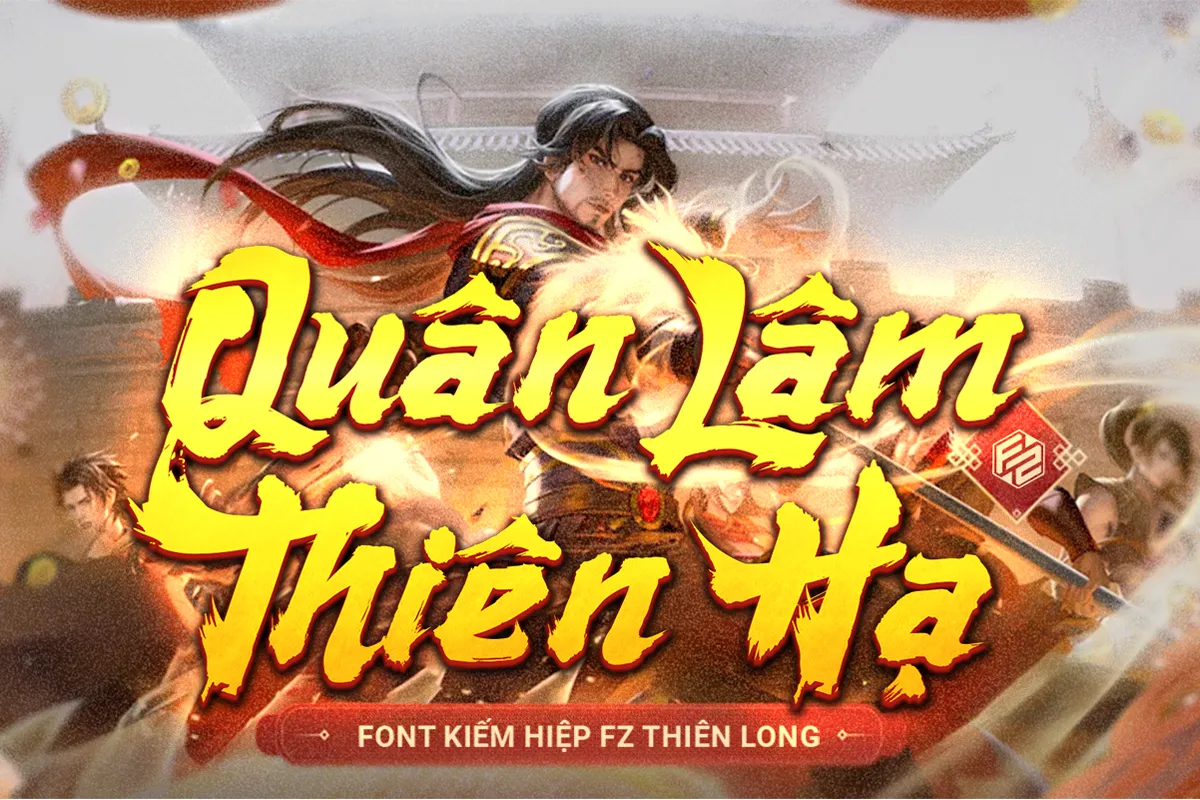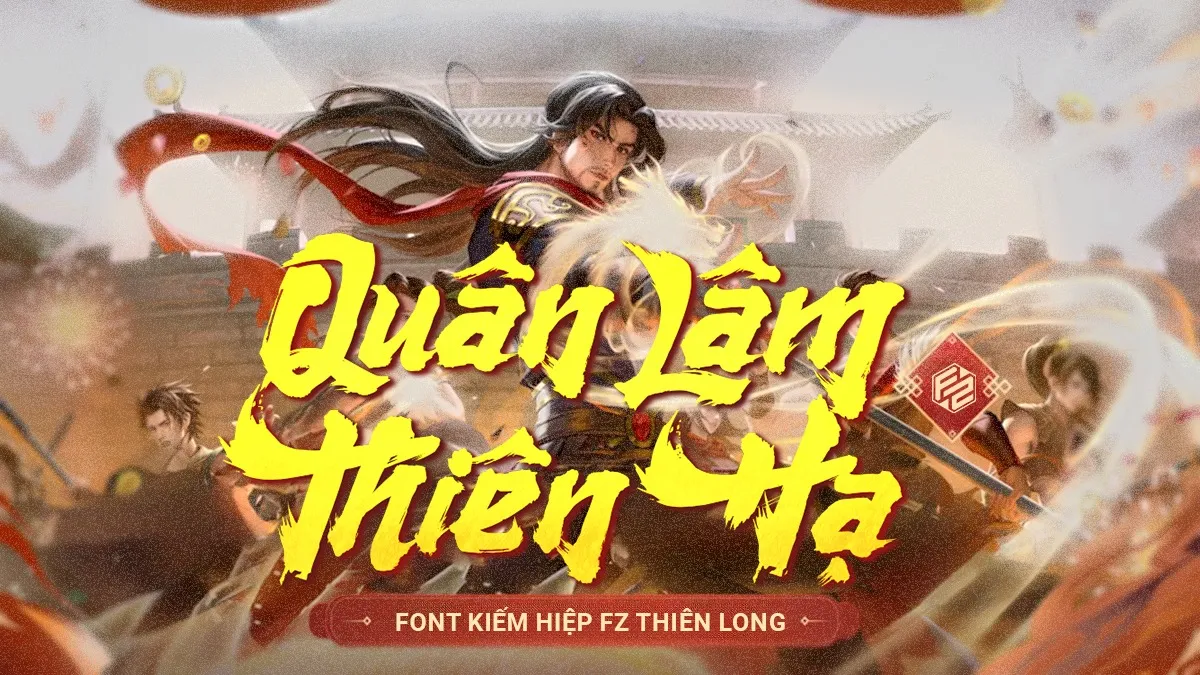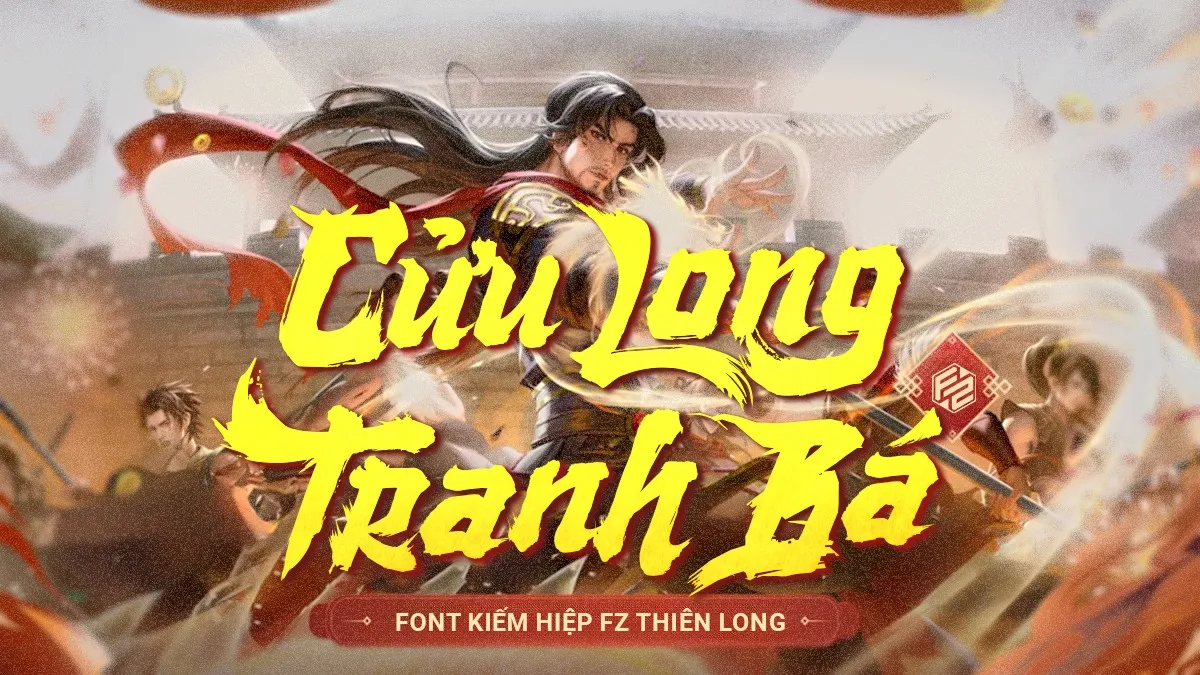
Font Game Fz Thiên Long
FZ Thiên Long là bộ font đặc biệt được Đức Thủy thiết kế riêng cho các sản phẩm mang phong...
FZ Thiên Long là bộ font đặc biệt được Đức Thủy thiết kế riêng cho các sản phẩm mang phong cách game kiếm hiệp – cổ trang. Với từng nét chữ phóng khoáng, mạnh mẽ, FZ Thiên Long không chỉ là một bộ font, mà là khí chất, là tinh thần “Quân Lâm Thiên Hạ” được thổi hồn vào từng con chữ.
Điểm nổi bật của font game Fz Thiên Long
- Phong cách thư pháp kiếm hiệp: Lấy cảm hứng từ bút pháp cổ truyền, từng chữ cái như vẽ bằng cọ lông, tạo cảm giác mềm mại nhưng không kém phần sắc bén.
- Hiệu ứng texture mực cháy: Khi bạn kết hợp với các tông màu của texture đặc biệt sẽ tạo nên hiệu ứng độc đáo và cực kỳ thu hút.
- Độ tương phản mạnh mẽ: Dày – mảnh rõ rệt, giúp tiêu đề trở nên nổi bật và khí thế trên mọi nền tảng hiển thị.
- Rất nhiều ký tự thay thế: Với số lượng ký tự thay thế 160 bạn có thể tự do sáng tạo với nhiều phong cách khác nhau với cùng 1 nội dung.